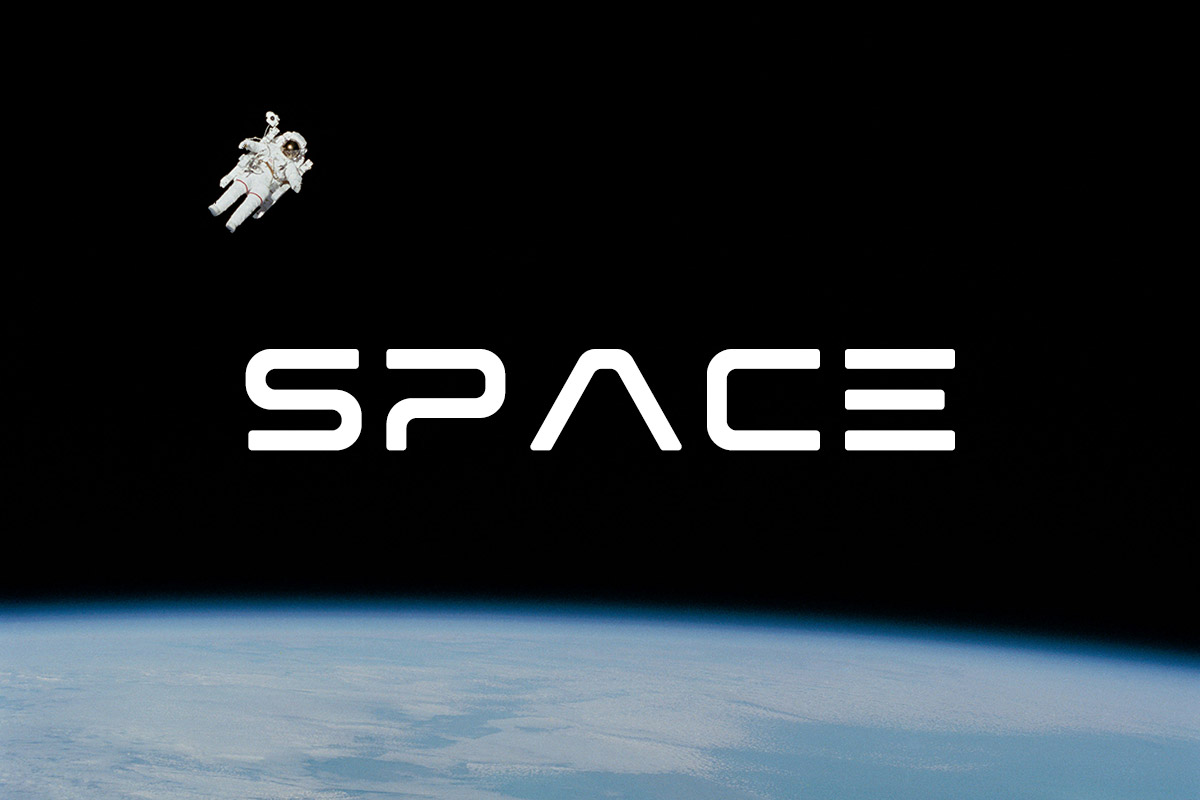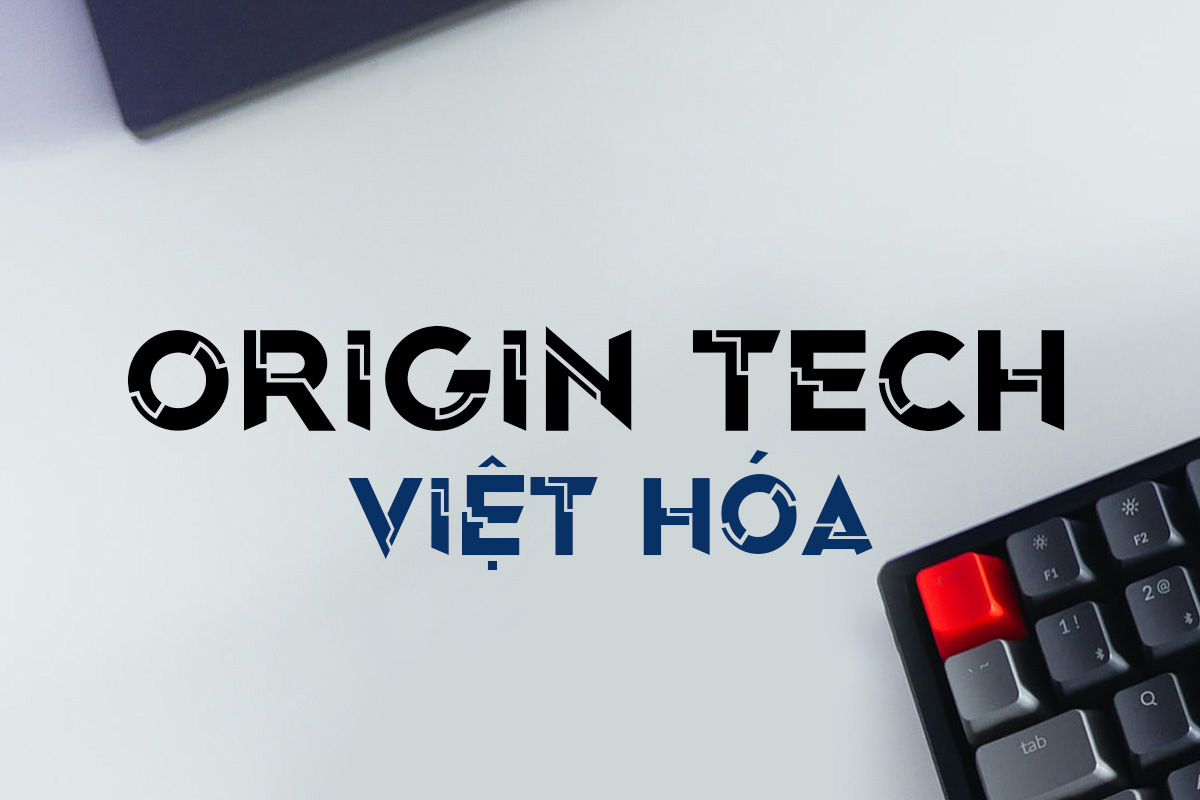
Font chữ công nghệ Việt hóa là nhóm phông chữ mang phong cách Futuristic (vị lai), thường sở hữu cấu trúc hình học (Geometric) chính xác với các đường nét tối giản và hiện đại. Nhóm font này gợi liên tưởng mạnh mẽ đến các bộ phim khoa học viễn tưởng, sự đột phá của trí tuệ nhân tạo và các thiết bị số tiên tiến. Doozypack.vn chia sẻ link tải font công nghệ Việt hóa chuẩn, hỗ trợ đầy đủ các ký tự tiếng Việt giúp bạn dễ dàng ứng dụng vào thiết kế bao bì điện tử, logo startup hay các ấn phẩm truyền thông đậm chất kỹ thuật.
Đặc điểm nhận diện của các bộ font chữ công nghệ hiện nay
Lựa chọn font công nghệ không chỉ là chọn kiểu dáng, mà là chọn cách thương hiệu thể hiện tầm nhìn và sự sáng tạo dẫn đầu xu hướng.
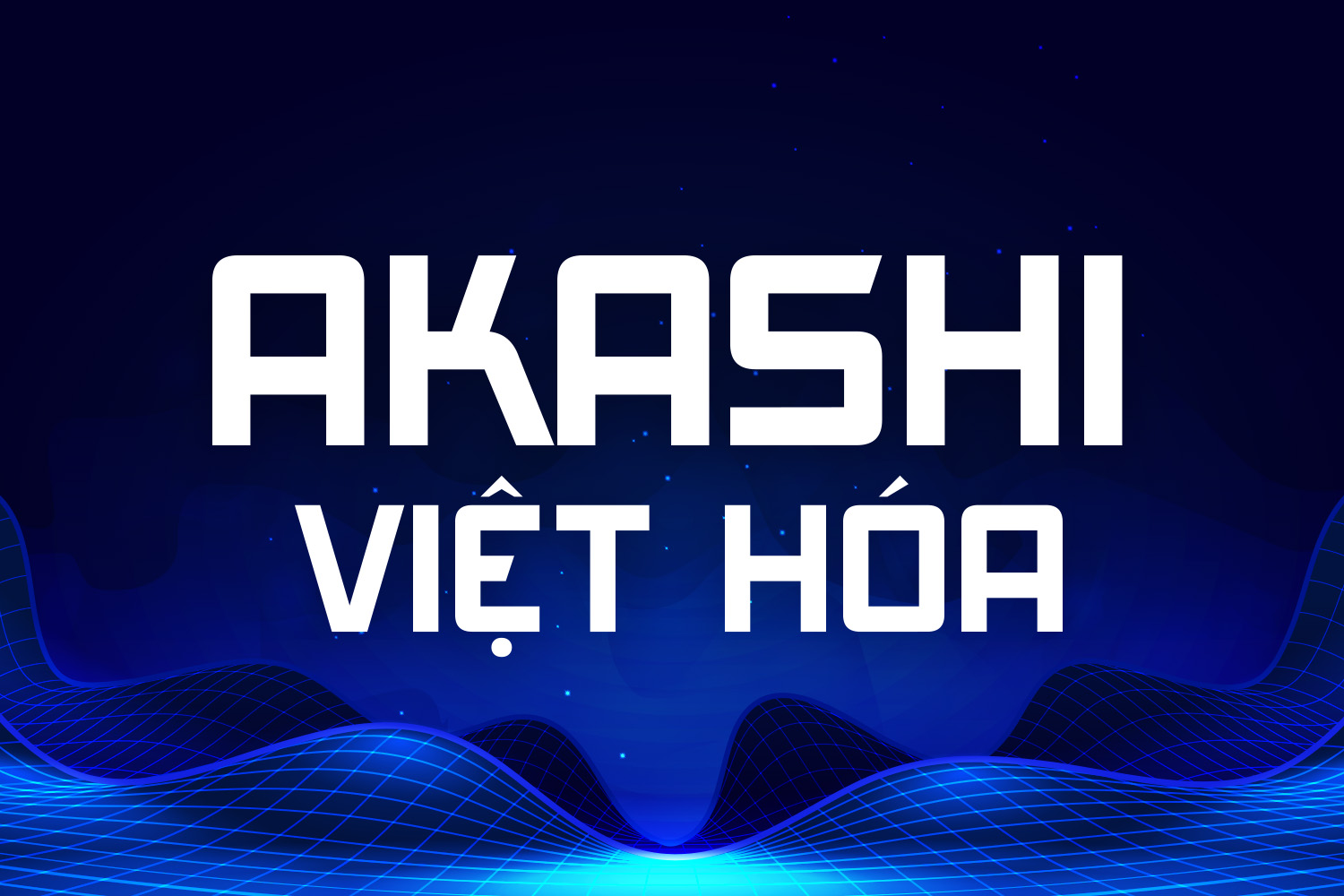
Cấu trúc hình học tối giản và chính xác
Đặc trưng lớn nhất của font chữ công nghệ là sự tuân thủ nghiêm ngặt các quy tắc hình học. Các đường nét thường vuông vức hoặc được bo góc bằng những bán kính cực nhỏ, tạo cảm giác về sự chính xác tuyệt đối như được lập trình bởi máy tính. Sự tối giản này giúp font chữ dễ đọc trên cả màn hình kỹ thuật số lẫn các bề mặt bao bì in ấn, mang lại vẻ ngoài sạch sẽ và chuyên nghiệp.
Cảm hứng từ tương lai và sự đột phá kỹ thuật
Nhiều bộ phông chữ công nghệ được thiết kế với cảm hứng từ giao diện điều khiển phi thuyền, mã code hoặc vi mạch điện tử. Những đường nét cắt vát táo bạo hoặc các ký tự có khoảng hở kỹ thuật giúp bản thiết kế mang tính “vị lai”, khơi gợi trí tò mò và niềm tin của khách hàng vào công nghệ vượt trội của sản phẩm bên trong.
Top bộ font công nghệ Việt hóa được đánh giá cao nhất
Dưới đây là một số gợi ý font công nghệ việt hóa được các designer ưu tiên sử dụng để tạo nên vẻ ngoài hiện đại cho sản phẩm:
- Font Exo / Exo 2: Một trong những bộ font công nghệ linh hoạt nhất với 9 độ dày khác nhau, từ thanh mảnh đến siêu đậm, phù hợp cho mọi vị trí trên bao bì.
- Font Michroma: Mang đậm phong cách cơ khí cổ điển nhưng vẫn rất hiện đại, thường được dùng cho các thương hiệu phần cứng hoặc máy móc.
- Font Orbitron: Phông chữ Sans-serif mang phong cách Sci-fi mạnh mẽ, lý tưởng cho các sản phẩm gaming, robot hoặc ứng dụng di động.
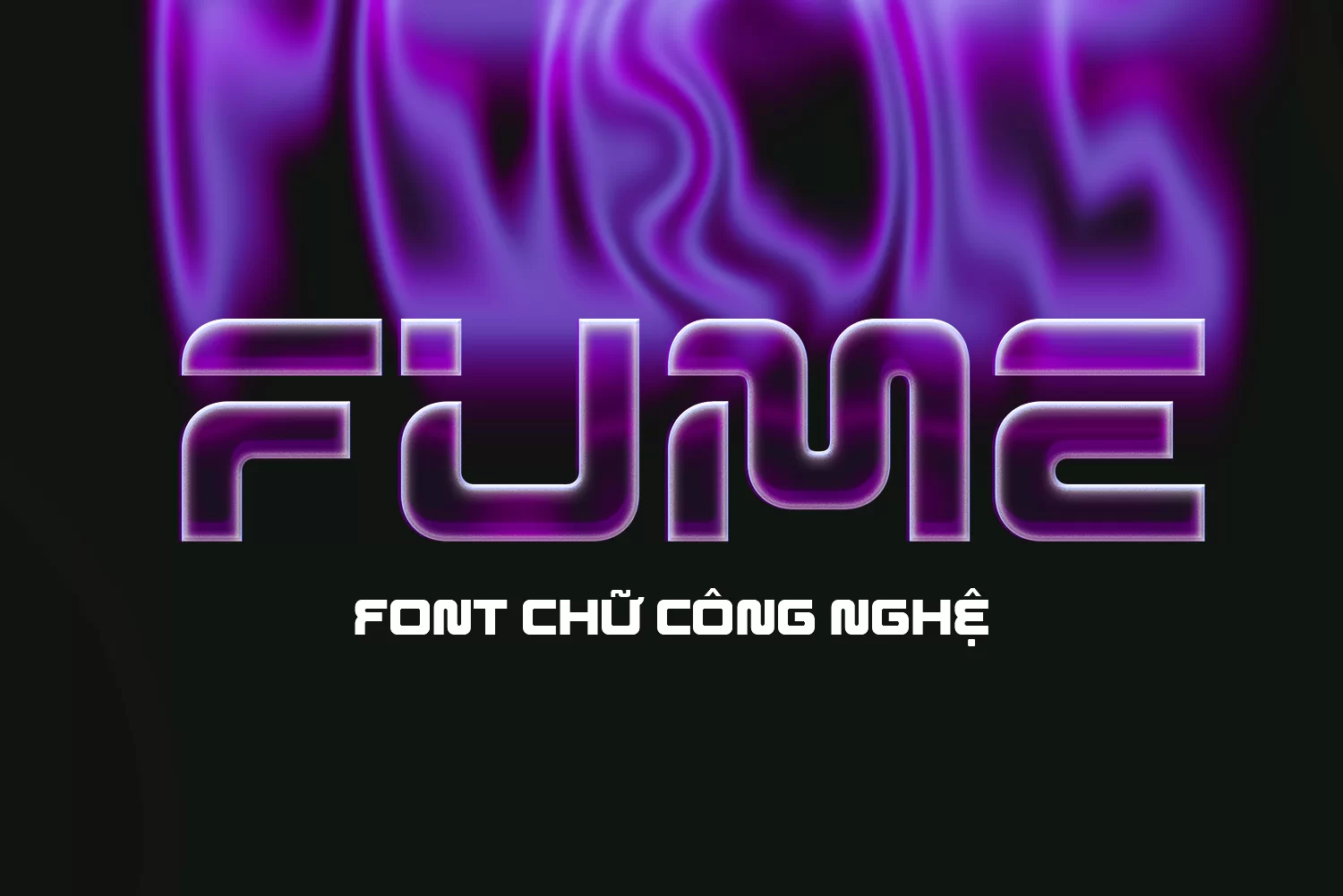
| Phong cách Font | Đặc điểm thị giác | Mục đích in ấn phù hợp |
| Geometric Sans | Hiện đại, tinh tế | Hộp đựng smartphone, bao bì phụ kiện thông minh, túi giấy tối giản. |
| Sci-fi / Futuristic | Phá cách, mạnh mẽ | Thiết kế logo gaming, hộp đựng đồ chơi robot, tem nhãn công nghệ. |
| Digital / Mono | Mộc mạc, đậm chất code | Bao bì linh kiện rời, nhãn dán kỹ thuật, tài liệu hướng dẫn phần mềm. |
Tư vấn từ xưởng in: Nếu sản phẩm của bạn hướng tới sự tinh tế, hãy chọn Exo 2 Light cho các nội dung phụ. Ngược lại, để tên thương hiệu thực sự nổi bật trên vỏ hộp, các style Bold hoặc Black của Orbitron sẽ tạo hiệu ứng thị giác mạnh mẽ hơn rất nhiều.
Ứng dụng của font chữ công nghệ trong ngành sản xuất bao bì giấy
- Hộp đựng linh kiện điện tử: Các thông số kỹ thuật được trình bày bằng font công nghệ giúp bao bì trông như một sản phẩm được nghiên cứu chuyên sâu, tăng độ tin cậy đối với người dùng.
- Túi giấy in logo cho startup: Tên doanh nghiệp được thiết kế theo phong cách Futuristic giúp túi giấy trở nên hiện đại và thu hút, khẳng định tinh thần sáng tạo dẫn đầu.
- Tem nhãn decal kỹ thuật: Các dòng font công nghệ có độ tương phản cao, giúp các mã QR hay mã hiệu sản phẩm trên tem nhãn luôn rõ nét và dễ quét.
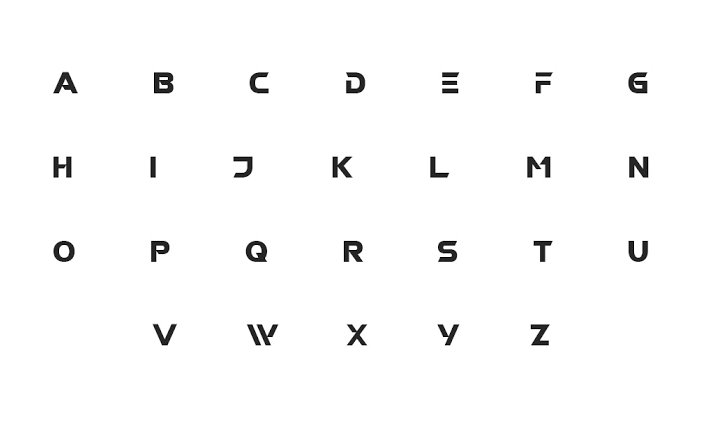
Lưu ý kỹ thuật khi in ấn font chữ phong cách công nghệ tại Doozypack.vn
Việc đưa thiết kế công nghệ vào sản xuất thực tế yêu cầu sự am hiểu về kỹ thuật in ấn để tránh các sai sót không đáng có:
- Xử lý hệ màu CMYK: Các thiết kế công nghệ thường sử dụng màu Neon rực rỡ trên màn hình (hệ RGB). Khi in ấn thực tế, các màu này cần được chuyển đổi sang hệ CMYK và điều chỉnh thông số để tránh bị xỉn màu, giữ được vẻ hiện đại của font chữ.